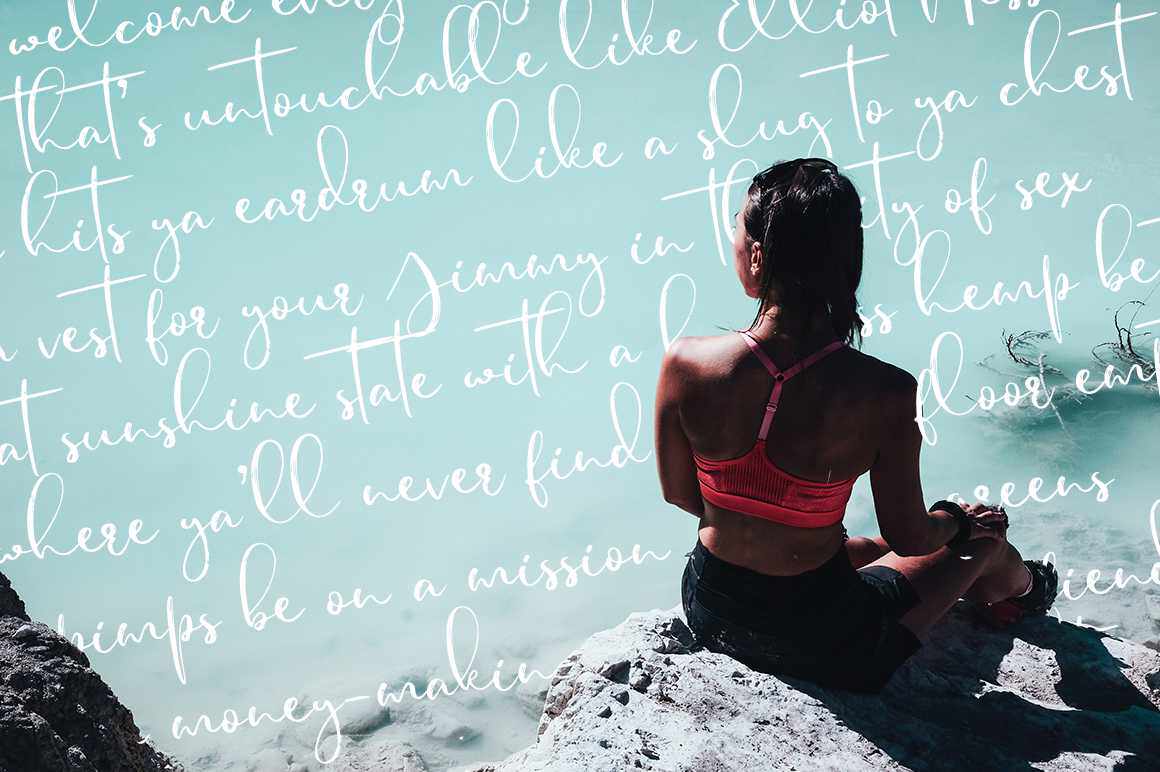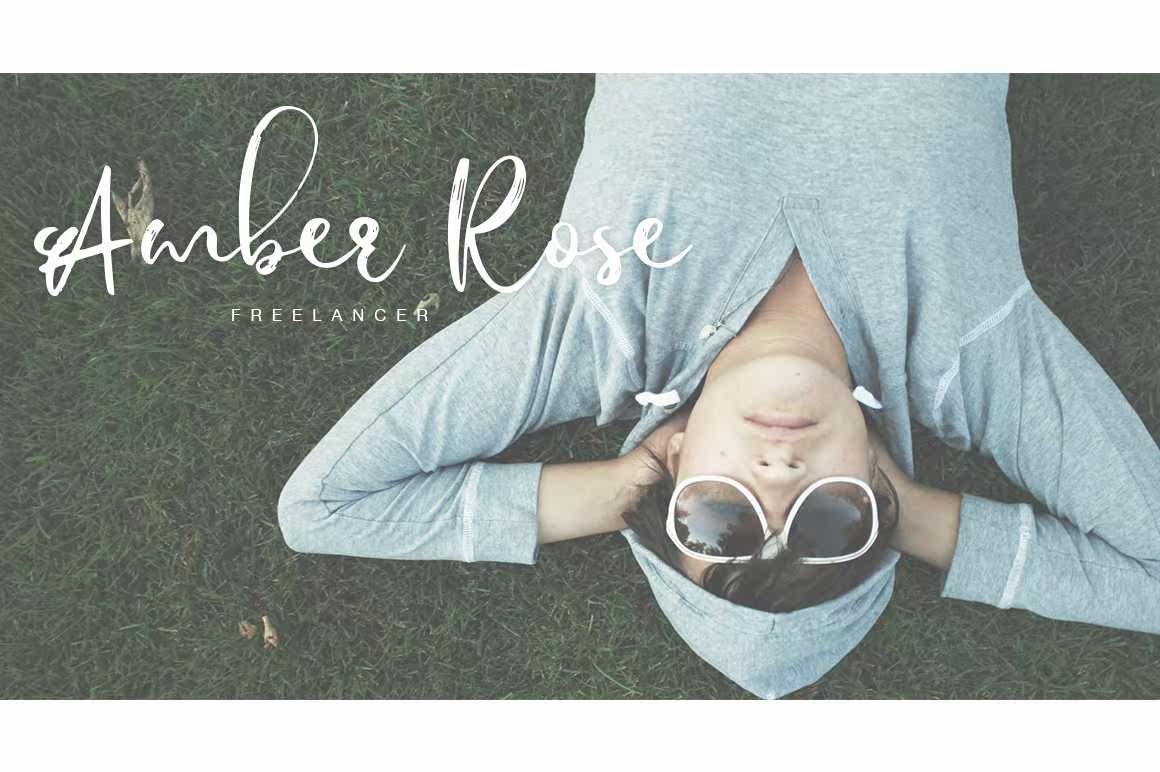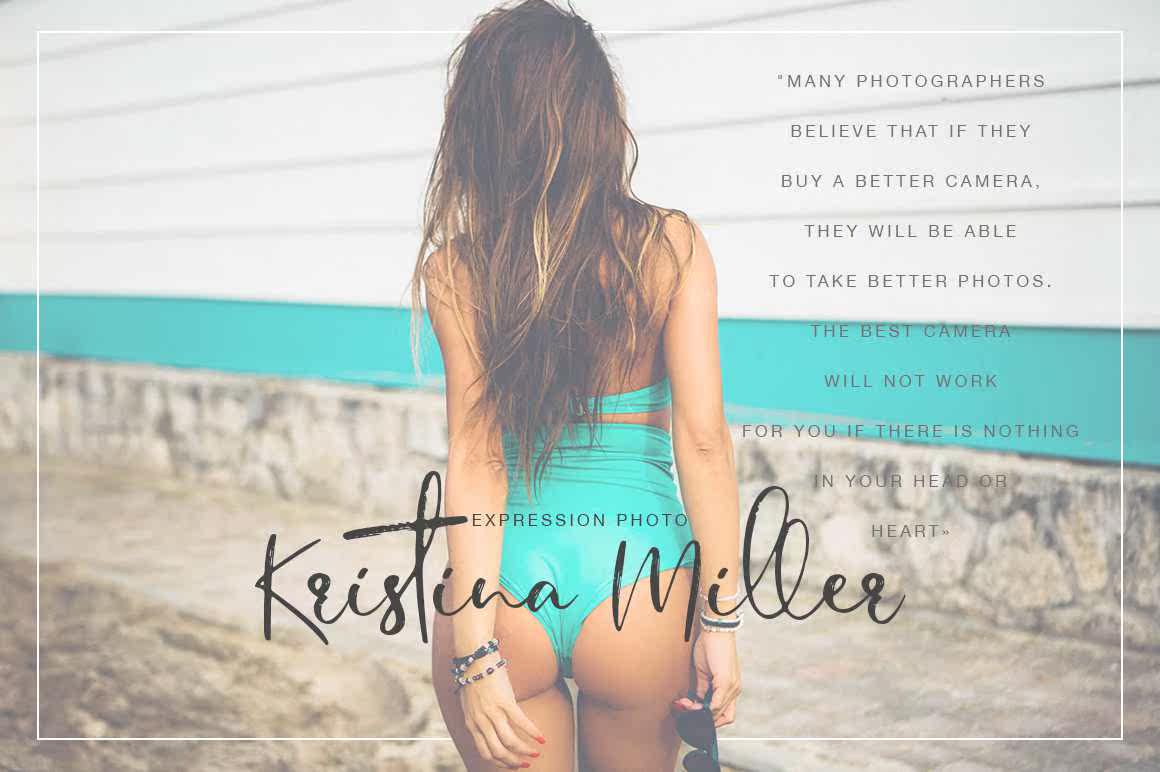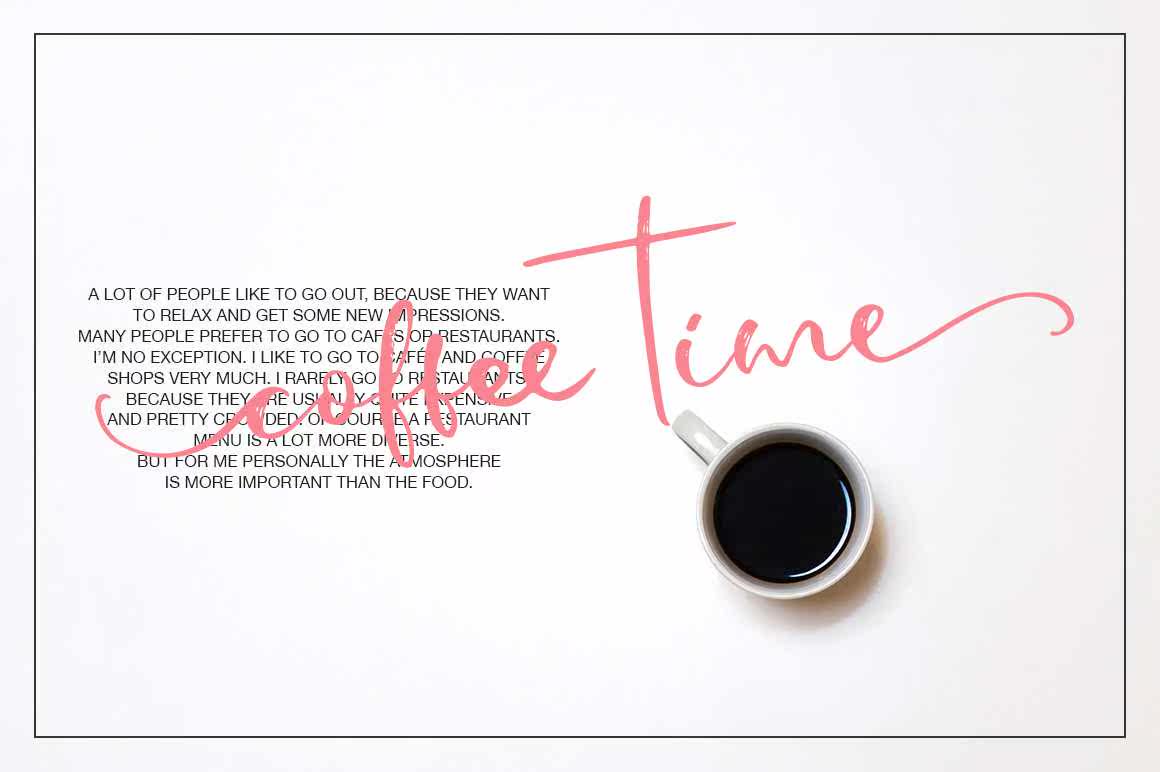
Jiguliny–一款全新的智能手机,适用于贺卡、品牌材料、名片、报价、海报等!这款FontarePerfectforWedding明信片。或者您可以为您的徽标、博客、文具、营销、杂志等创建完美而独特的设计:)功能:Jiguliny–一款全新且精确的字体。非常适用于贺卡、品牌资料、名片、报价、海报等!此FontarePerfectforWedding明信片。或者您可以创建完美且独特的徽标、博客、文具、营销、杂志等设计:)功能: